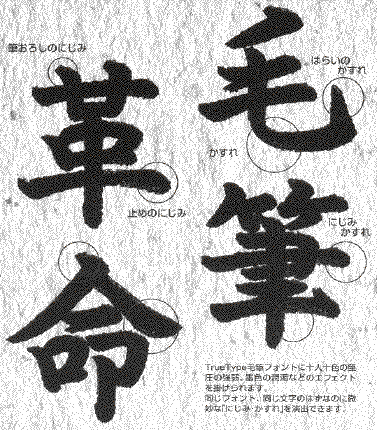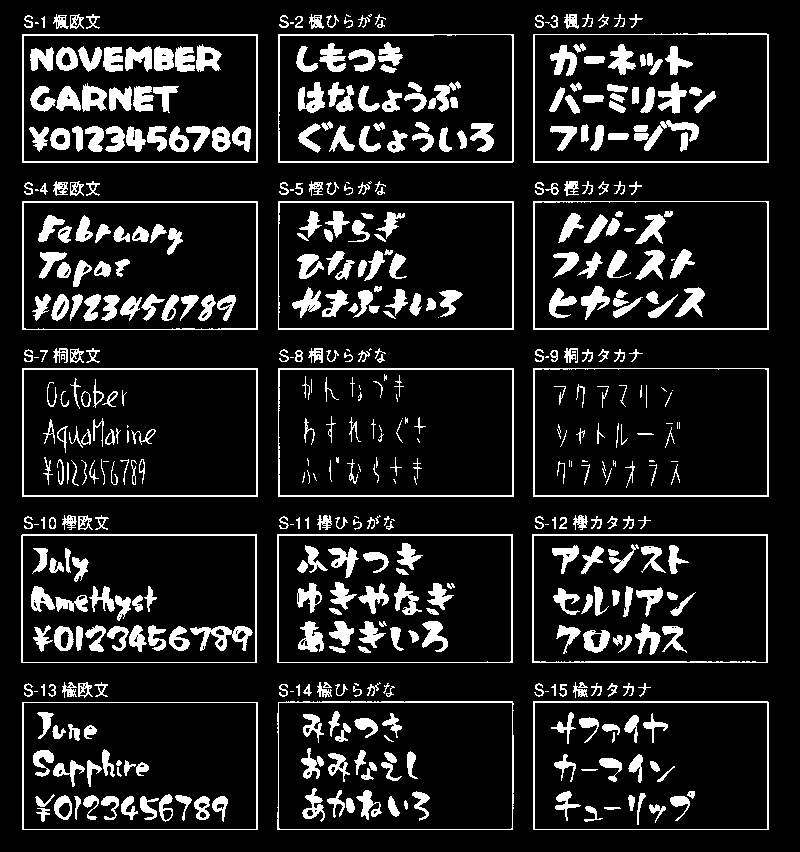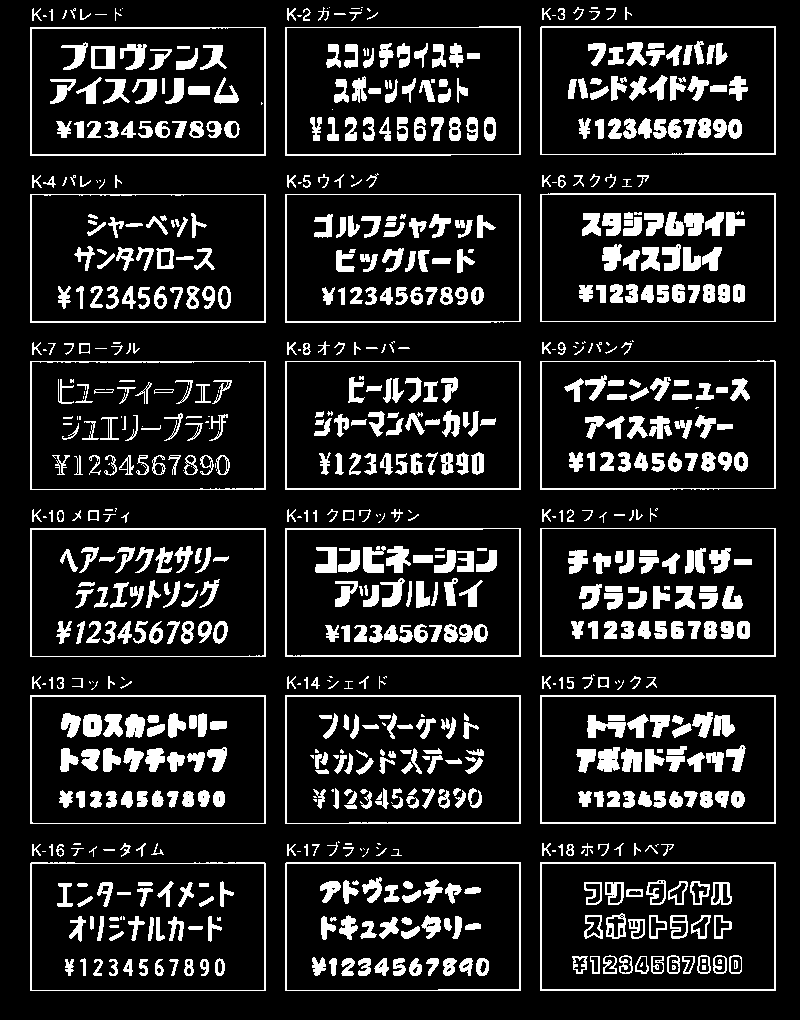
そして、この機能を使いたいテキスト部分を選択(反転状態に)してから、フィルターメニューからテキスト→タイプミキシングを選ぶと、設定用のダイアログウインドが現われます。
漢字・ひらがな・カタカナ・約物・欧文それぞれ任意の書体を設定し、OKすれば終わりです。1ブロックのテキストを一度で組み合わせられるので、何度でも気楽に変更し確認ができます。
「タイプミキシング」はフォントワークス社が1995年秋に、かな書体を発売したときに製品に添付されたものなので、フォントワークス書体のユーザ以外にはあまり知られていない(もっと宣伝したほうがイイと思うヨ)のですが、他社の書体(漢字も含め)でも問題なく使え、Illustratorを多用するデザイナーにはとても重宝なプラグイン・フィルターです。
印刷業界(プロの世界)では基本的に、大量に印刷配付するためのクセのない汎用性の高い書体が必要だから、開発にとても時間を掛けた洗練された毛筆書体が好まれる。
それに較べ、パソコンで毛筆書体を使用する人達は、プライベートな肉筆の代用目的で、毛筆書体を使用するようだから、活字や写植の原字からパソコン用に移植された、完成度が高くキレイに整った書体よりも、肉筆感があり少しやぼったい書体を好むようだ。
開発する側から見れば、書家に発注すれば短期間に原字が完成する毛筆書体は、考え様によっては安上がりな書体な訳だ。
安上がりな毛筆フォントは洗練されてはいないが、温かみのようなものを感じる。決してウマク書体化されている訳ではない。
手書き本来の毛筆の味わいを、書体製品として再現するのはかなり大変なことだ。
プロポーションの問題、文頭・文中・文末などでの字形の変化や大小、墨の含み加減やかすれ・にじみ。そして強弱の問題など。
フォントの最先端技術の話題では、実現可能な様に思われているが、誰も本気ではやっていないのではないか?
書家、書体デザイナー、ソフトウエア技術の三者がうまく絡み合って初めてそこそこのものが出来るのだと思う。
そんな本気の毛筆感覚の再現ではなく、もう少し気楽に毛筆の雰囲気に近付けましょうというのが、今週紹介する「毛筆新技術」だ。
毛筆はがき印刷ソフト「はがき専科」という商品の説明文から抜粋すると…
●きれいなだけのワープロ文字からと、とても面白そうなのですが、このソフトは残念ながらWIndows用なのだ。
あなただけの個性輝く文字に変化!
●個
人個人、一筆ごとに文字が自己主張している
本当の毛筆です。
●TrueType毛筆フォントに十人十色の筆圧の強弱、墨色の潤渇などのエフェクトを掛けられます。
●同じフォント、同じ文字のはずなのに微妙な「にじみ・かすれ」を演出できます。
●欧文用フォントと基本的に同じ仕様で作成されているため、OSやソフトウエアのアップデートに影響されない。
●2バイト文字に対応していないアプリケ-ションでも使える。
●データ量が小さく、コピープロテクトがないので、違法コピーが簡単にできる。
最後の、違法コピーが簡単にできる便利さが、私にとってはツライ!
コピープロテクトが施されていないソフトウエアは自由にコピーして使って構わない、と思っている人達がなんと多いことか? たぶん、販売元からの出荷報告の10倍以上が、違法コピーされているのだろう。
私のところへ、こんな書体が手に入ったよ(買ったのではない)と、私が作者とも知らずに報告する輩まで出てくると本当にイヤになってしまう。
私がこの方式での書体提供を2書体で中止した理由だ。
使う側にとっては便利な、1バイトの日本語かな書体。ビジネスとして成功するのだろうか?
もちろん私は成功するようなモラルのある社会になって欲しいし、そうならなければ誰も新しい書体なんかデザインしなくなる。
趣味で書体を使う一般の人達より、仕事として書体を使うデザイン・印刷業界の人達のモラルの方がヒドイと私は感じている。
彼らはデザイン・印刷を商品に経済活動をしているわけだが、商品として販売されているソフトウエアを勝手にコピーして使うことが、画材店でロットリングやインスタントレタリングを万引きしたり、他人の倉庫から紙を盗み、それらの道具や素材を利用して仕事を完成させ、クライアントに納めるとんでもないドロボー行為だと気づいていないのだ。
フォント・トゥーから発売されたこのシリーズも、そんなモラルの低い人達に違法コピーされないことを祈ります。
残りの「カナシリーズ」の紹介です。
親しみやすいレタリング、という感じのカタカナと数字のみのシリーズで色々と使い道がありそうです。
私自身はプログラム的なことは解からないので2バイト対応にできず、この書体専門に文字をキーボード入力をしなければならないのが欠点だったが、横組に関してはプロポーショナルスペースで組まれ、カーニングペアも設定してある、当時としては高機能なフォントだった。
その後、同じキーマップを利用して、静岡のほうのR研究所とかいう会社が、女子高校生達に作らせたポップなフォントを、千円か二千円で販売していたが最近はあまり見かけない。
文字入力の問題も、普通の2バイトの文書を仮名だけ、この書体の1バイト文字に変更する、ハイパーカードのスタックを作って解決した人もいたようで、R研究所のフォントにバンドルされていたような気がする。
そのまま、この1バイト書体のキーマップが普及して、かなフォントフォーマットの一種として定着すれば良いなあ、と思っていましたが、しばらくして本格的なPS書体が、あちこちのフォントメーカーから続々と発売されたので、このタイプの日本語かな書体は忘れられていきました。
ところが、最近このタイプのかな書体が、また発売されました。
フォント・トゥー オリジナル1バイト書体 DESIGNER'Sという製品です。
二つのシリーズがあり、今回はシリーズ「墨」を紹介します。
墨で描いた手書き風文字を、風合いを損ねずにデジタル化した究極のディスプレイフォントだそうです。
印刷物制作時に(たとえば新聞広告やパンフレット)、本文の内容が決定していないのだが、完成時のデザインが見たい場合、その本文部分を何らかの方法で、ここにこのぐらいの量の文章が入りますと体裁を作らなければなりません。
昔は、ペンやロットリングで描いた2本線や、グレーのマーカー(マジックのようなもの)で線を描き、1行分として表していました。
その後、関係者の想像力が欠如していったためか、もっとリアルに文章をイメージさせようと他の印刷物の文章部分を切り取って貼り込んだり、コピーして使いだしました。
さまざまな文字サイズ・行間を網羅し編集した専門の本まであったような気がします。
しかし、そこにリアルな文字が並んでいるとつい読んでしまうのが人間です。あくまでも体裁を整えるためだけに貼った、企画とまったく違う内容の本文を読み取って驚いたり苦言を呈する人もいたのでしょう。一般的ではないかも知れないが、私が見た例では文章をデジタルコピー機で鏡像(左右反転)にし、ワザと読みにくくしているものもありました。
このように、デザインや印刷の業界では、ここに文章があるということが判るが、その内容が読めてはいけない文字らしきものが必要なのです。
最近のDTPソフトでは、文字のサイズや行間はいくらでも自由になるので、あとは書体です。それが、レイアウト用疑似文字「JTCギジモ明朝」書体なのです。想像できますか? ご覧になってください。
世の中には本当に色々な書体があるものです。Mac用のPostScriptフォントとして販売されていますが、明朝だけでなくゴシックも開発されるかもしれませんね。
日本タイポグラフィ年鑑1987に、カンプ用コピーインディケーション・シートとして発表された書体が、改良され製品化されたものと思われます。
そしてマル文字といえば漢字はナールを使うと思いがちだが、この書体はナカフリーがぴったりで、マル文字とは言い難い書体だ。
ウマイデザイナーが技術の確かな写植オペレータと組み、キレイに詰め印字すれば、この現代的筆記書体を使いこなせる。
少し不運だったのは、一般からのコンテストで入選し、採用されたマル文字書体と同じような扱いを受けた事だ。
エツール、イクールなどのコンテスト採用書体は、応募された原稿に(適当な紙に好きな筆記用具で両仮名を書けば良かった)何もプロ的な処理を加えずに製品化されたので、それはそれは…ヒ◯イものだったから。
彼女自作のCGが20点、スクリーンセイバー50点、そしてTrueTypeフォント「恋文 千葉麗子」が収録されている。
フォントの文字数は一般的に使用される文字をピックアップしたという4005文字。
一日か二日で書き飛ばした原稿から、単純にフォント化しただけのモノだから、書体の品質としてはヒドイ。しかし、まさに手書きそのままの生書体だから、たとえば若者向け雑誌の投稿欄などをこの書体で組めばそれなりのフンイキはでると思う。